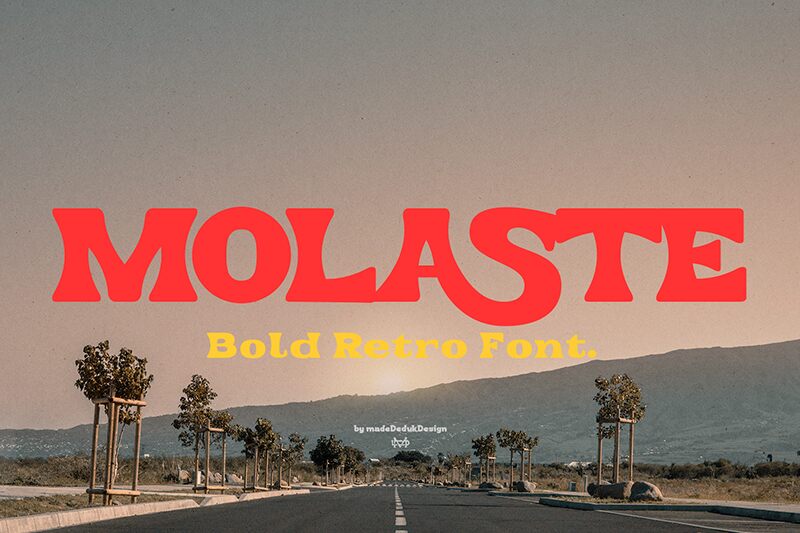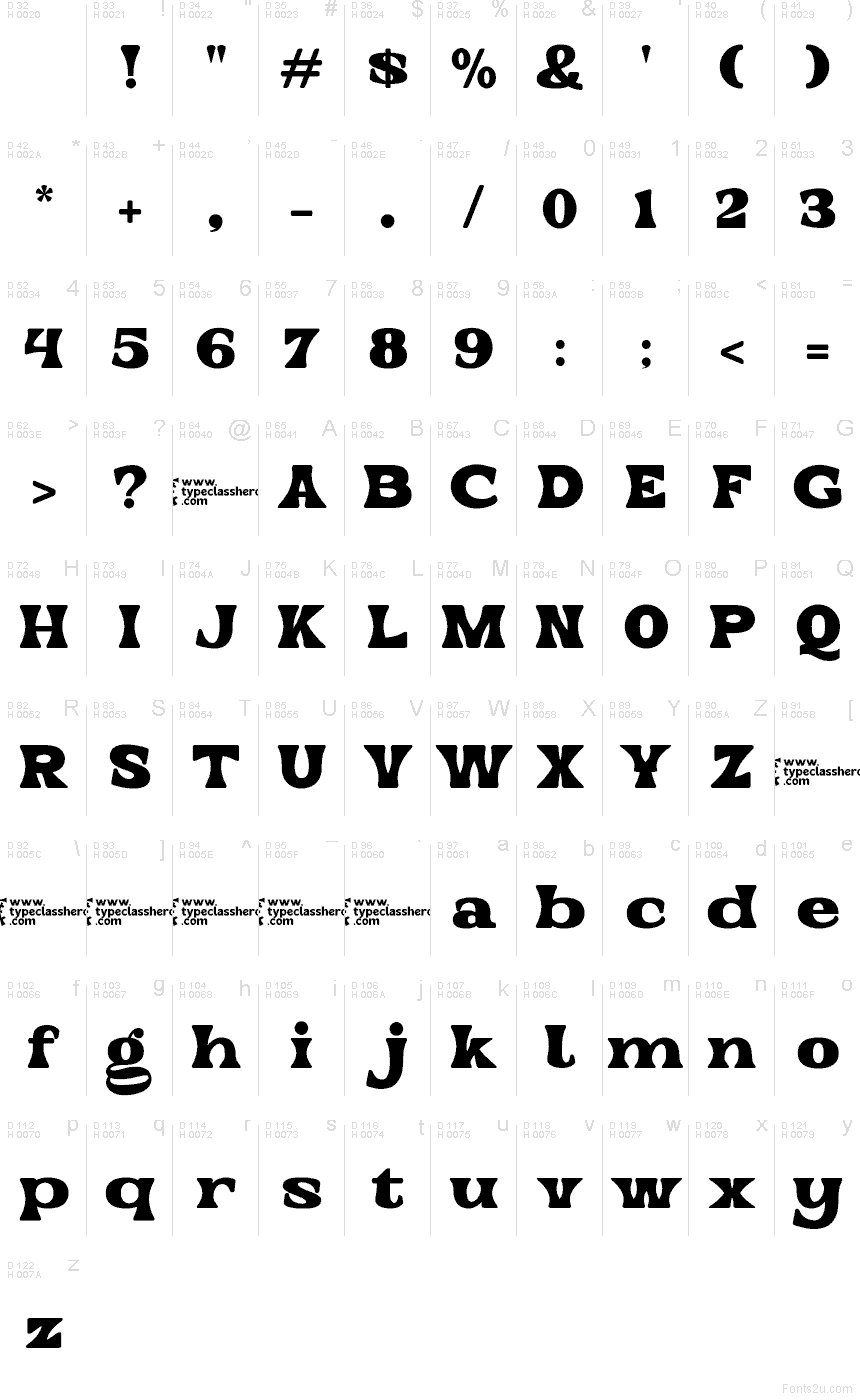
Molaste od Suandana Ipandemade je bezplatné retro písmo typu display, které definují široké, plné tahy a jemné vnitřní zářezy. Ty dodávají písmenům vyřezávaný vzhled připomínající plakáty ze 70. let. Zaoblené patky a klesající křivky vytvářejí pomalý, důrazný rytmus, díky čemuž font působí spíše jako nápis na stylovém baru nebo obal hudebního alba než jako pouhý retro revival.
Tento charakter se skvěle hodí na obaly produktů, hudební grafiku, branding kaváren, plakáty na akce i nadpisy, které vyžadují hřejivý, nostalgický nádech. Široké křivky a měkké hrany jsou ideální také pro skici log a příspěvky na sociální sítě, kde trocha nostalgické jemnosti působí lákavěji než ostré, moderní písmo.
Prezentace a vizuální ukázka písma Molaste Demo Regular
Mapa znaků písma Molaste Demo Regular
Mapa znaků písma Molaste Demo Regular: Základní latinka, strana 1
Glyfy písma Molaste Demo Regular — Základní latinka, strana 1